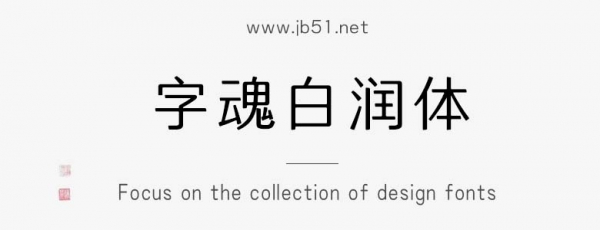
字魂白潤體由字魂字庫推出的黑體字體,該字體包含7144個中文、字母、 符號和數(shù)字,具有優(yōu)雅端莊的風(fēng)格,,適合應(yīng)用于藝術(shù)設(shè)計、平面宣傳設(shè)計、網(wǎng)頁設(shè)計,書法字帖等領(lǐng)域。
字魂白潤體字體是一款商用的黑體,圓體,基礎(chǔ)黑體字體,該字體包含7144個中文、字母、 符號和數(shù)字,具有優(yōu)雅端莊的風(fēng)格,可以滿足您設(shè)計上的各種需求,該字體主要用于電商直播等場景, 您不但可以在字魂網(wǎng)下載字魂白潤體字體,同時還有眾多毛筆書法字體、創(chuàng)意字體等可供選擇!